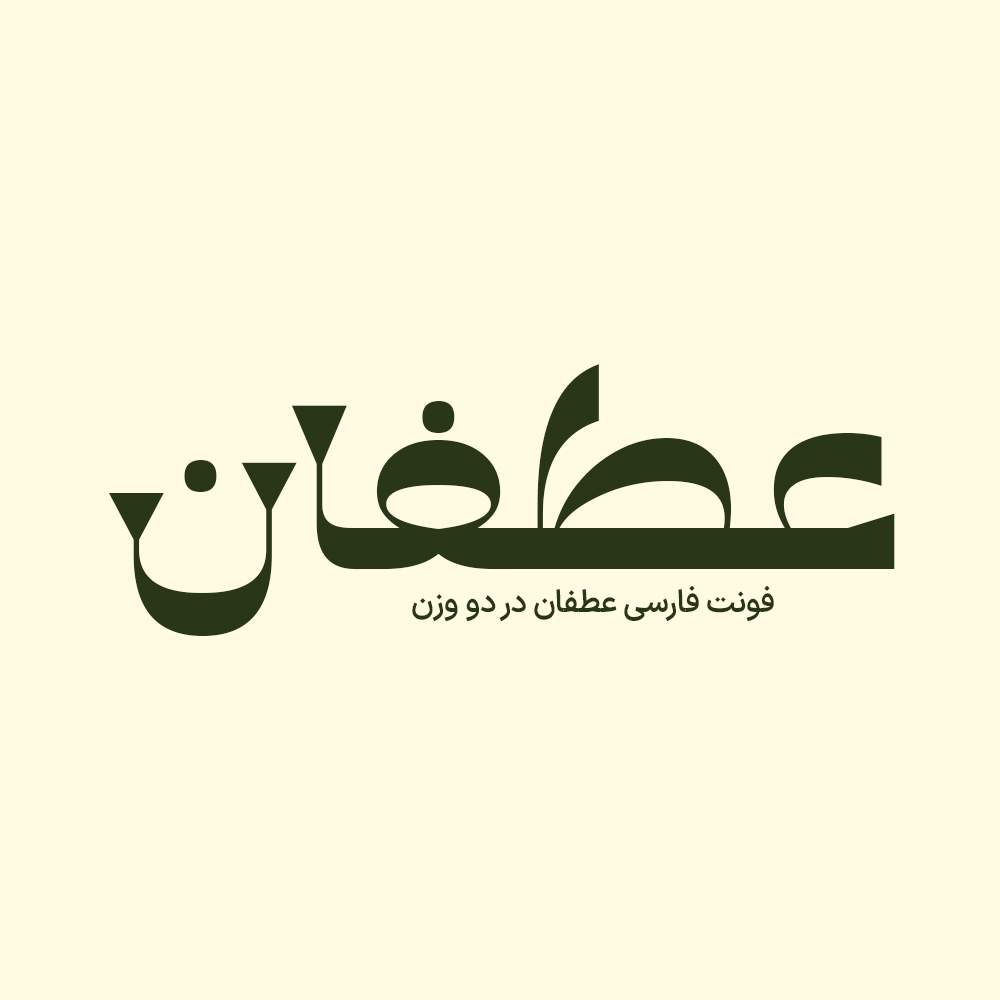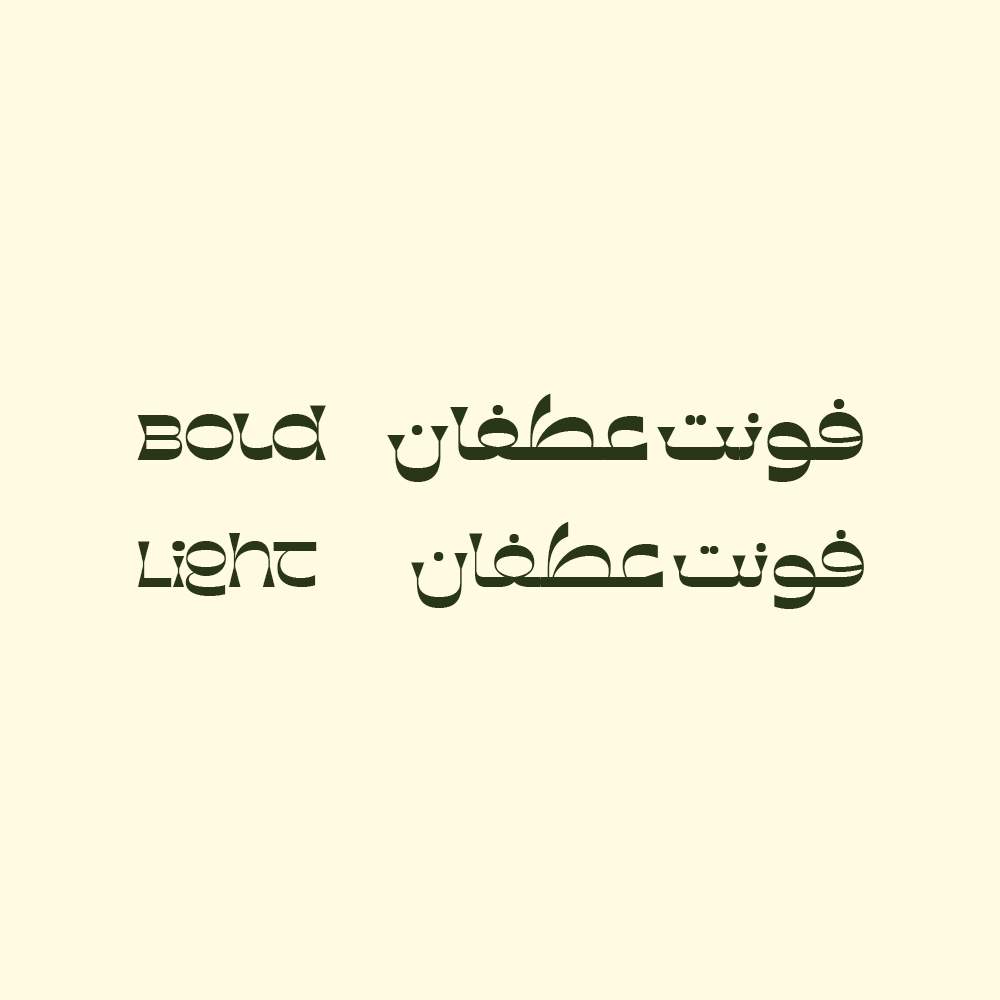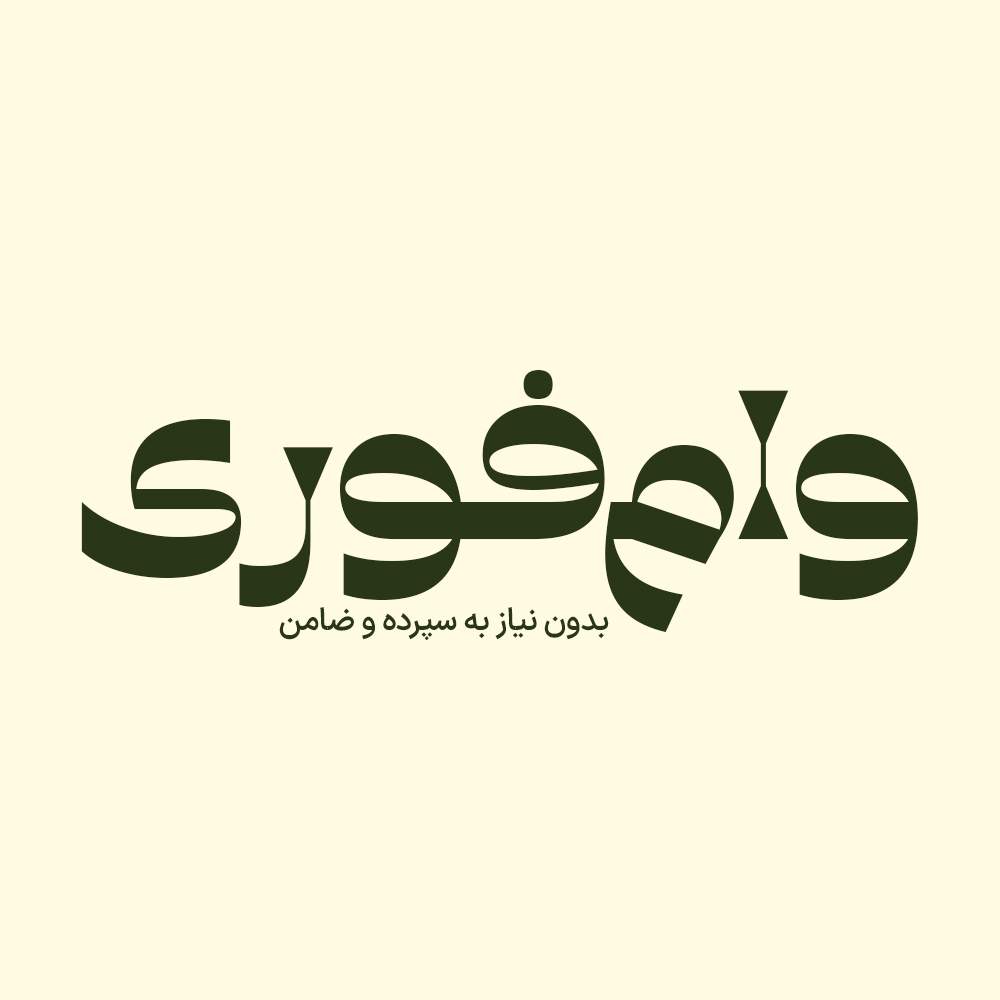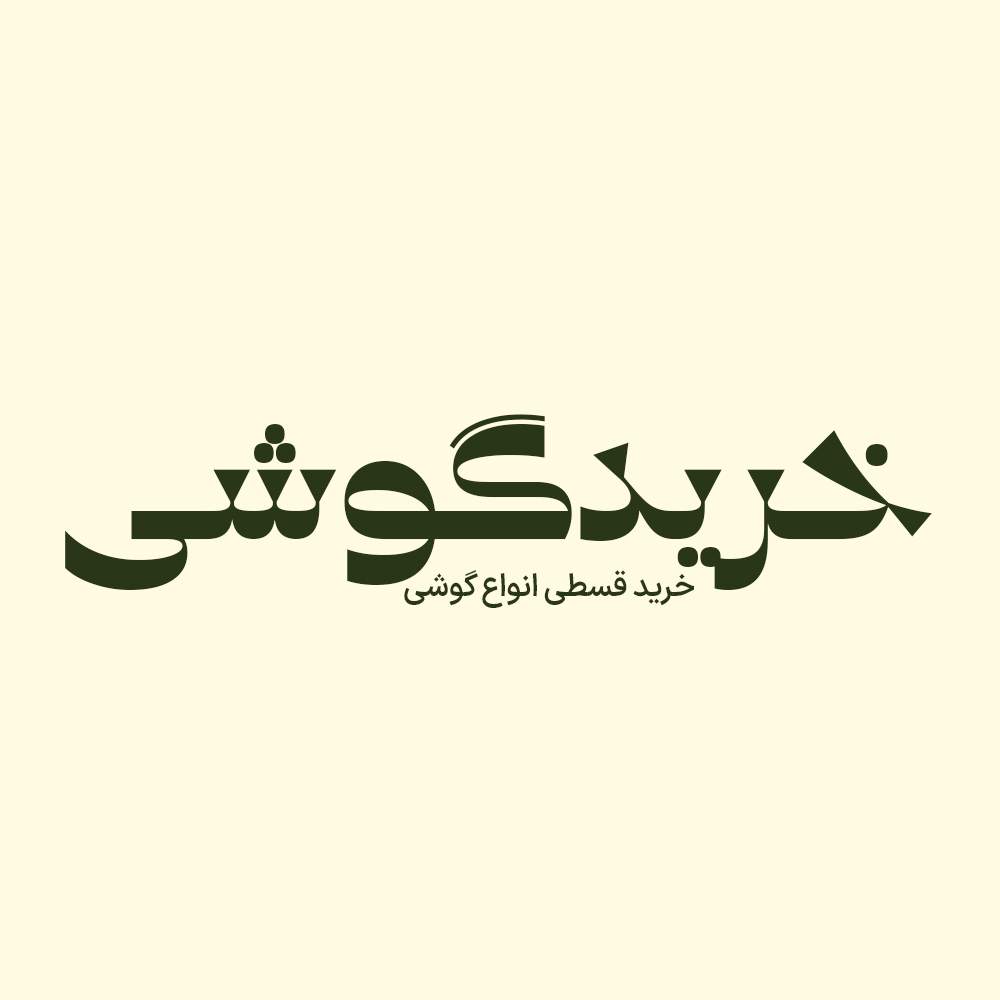
فونت فارسی عطفان Atfan Font
فونت فارسی عطفان دارای 2 وزن و برای طراحی‌های مختلف همچون کتاب و تولید محتوای متن‌های کوتاه و بلند می‌باشد. فونت قطار با ساختار حروف خود مناسب استفاده در تایپ‌های نوشتاری می‌باشد. فونت فارسی عطفان زیبا و حرفه‌ای مناسب استفاده در عناوین و تیترها و جملات بلند و کوتاه و هم طراحی انواع تکست‌گرافی و استفاده در طراحی های خاص می‌باشد.
• مناسب طراحی بسته بندی ها و چاپ
• فونت ویژه تبلیغات محیطی
• فونت طراحی کاور اینستاگرام
• فونت حرفه ای برای تولید محتوا
• فونت فارسی طراحی وبسایت
• فونت طراحی لوگو تایپ فارسی
• مناسب استفاده در تابلو های چلنیوم و طراحی حروف
پیشنمایش و نمونه تایپ های فونت عطفان